中文汉字的结构复杂、数量巨大,这为汉字创意对字体的设计与应用提供了更多的启迪和发展空间。汉字创意字体设计作为现代设计中最重要的组成,深化了文字的内涵,受到了人们的追逐和热捧。为更好的发挥汉字创意字体的作用,本文整理、归述了一些汉字创意字体设计原则,探讨汉字创意字体的应用方式。
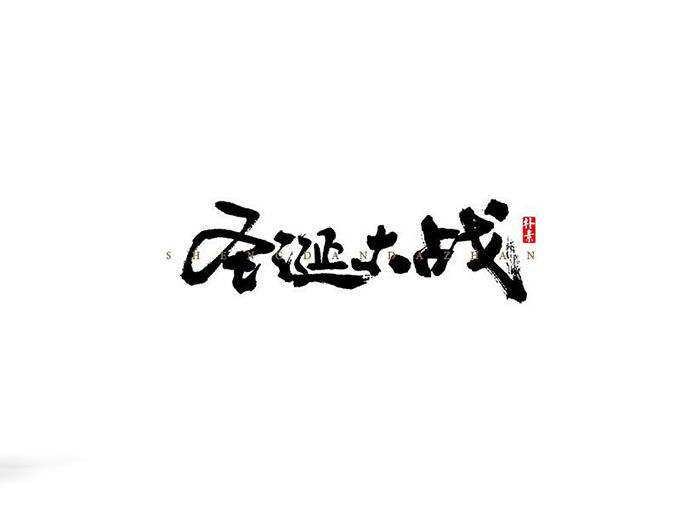
汉字设计需遵循的原则
汉字创意历经发展,由原始的象征图形逐渐演变至文字符号,是一个逐层递进的过程。通过对汉字创意中字体设计发展所蕴含的规律进行探寻,归纳了一些汉字设计原则,来指导设计及应用。
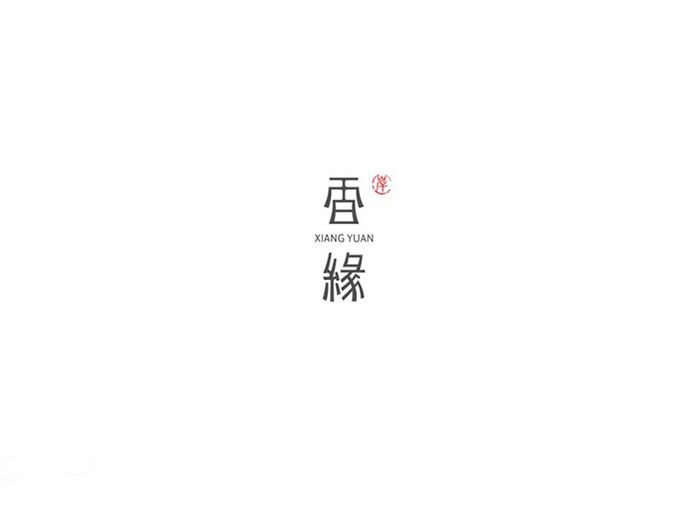
视觉平衡
汉字创意字体设计作为视觉设计的重要部分,设计中需要遵循视觉平衡原则,以塑造作品的美感。主要使用在字体笔划及结构的设计上,笔划运用是字体设计的初始,是决定字体设计风格的主要因素。汉字创意中字体的构成形式多样,通常会依据作品风格的需要而变化,从而形成了其独特的风格。目前,汉字创意字体设计的变化方式主要有叠加、突变、旋转等。
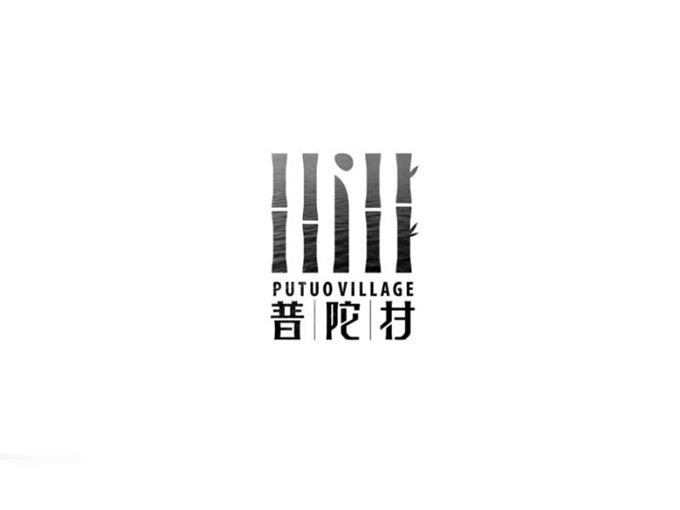
为保证汉字的可辨识性,无论哪种字体设计都应遵循视觉平衡的原则,从而设计出人们看得懂,但又不失新意的字体;字体的结构是设计的关键,基本由点、线、面三个要素构成,讲求匀称、和谐。在字体设计时,只有遵照形式规则将字体结构设计与图形视觉的美感有效的融合在一起,才能使创意汉字更具艺术魅力,展现得体而优美。这一规则就是视觉平衡,这既是汉字自身结构的规律使然,又是符合视觉审美需求的重要表现。
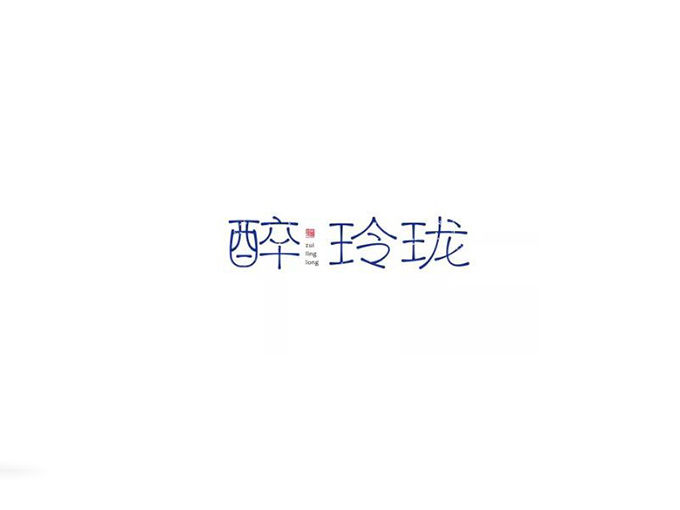
结构得体
字体的结构是汉字创意字体设计中需要着重考虑的因素,其均匀与否很大程度上取决于字形结构。为确保笔划分布均匀,需要兼顾正形呈现与负形空间,来实现字体设计应有的审美价值。创意设计要合理的进行笔划布局,巧妙的将元素穿插在一起,以尽可能的均衡正负形。
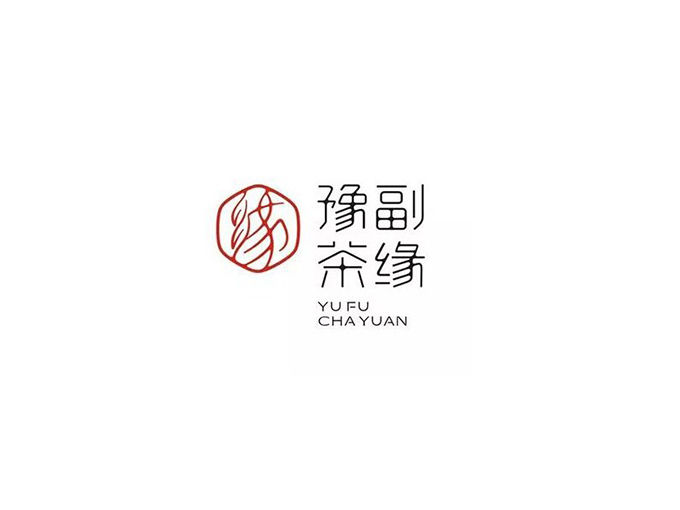
为考虑字形和笔划疏密过大,而避免造成字体结构出现给观众在阅读上带来的误差。因此,合理分析华人的汉字阅读习惯,必须提升设计字体的观赏性,要合理的调整汉字笔划,统一字形和字体大小,使得字体设计笔划得体,结构均匀。
重心稳固
重心稳固与否是衡量汉字创意中字体设计审美的标准之一,会直接影响到字体的可识别性。当字体设计重心稳固时,字体的可识别性强,有助于人们顺畅、舒适的阅读。反之,字体设计重心不稳固则可能会致使人们的视线在视觉范围内上下滑,给人们的阅读造成了一定的困扰,容易产生疲劳感。
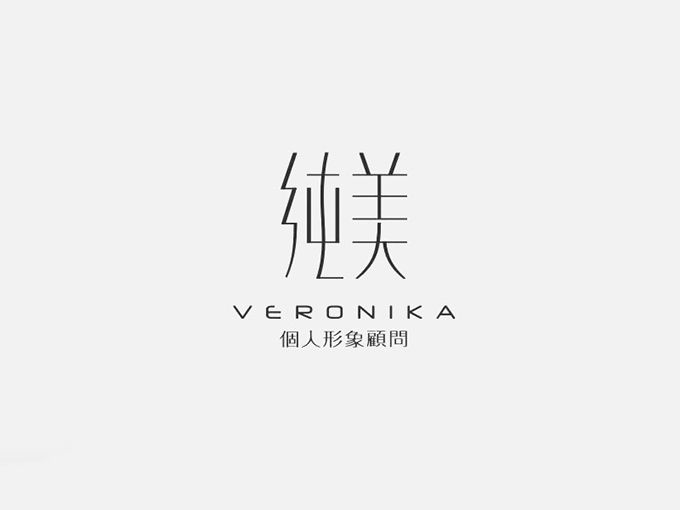
相对于西方文字,汉字的结构特异性强,内涵信息更丰富,要在不断的实践探索中,认真分析、总结以往的设计经验,来正确处理字体重心。另外,重心稳固原则还需要处理好字体重心与字体中心的内在联系,两者即有不同却又存在着必然的联系。纵然汉字字体的书写笔划略显复杂,但可以通过寻找字体外形和中心的方式,确立汉字重心结构,继而实现轮廓内部结构稳固。
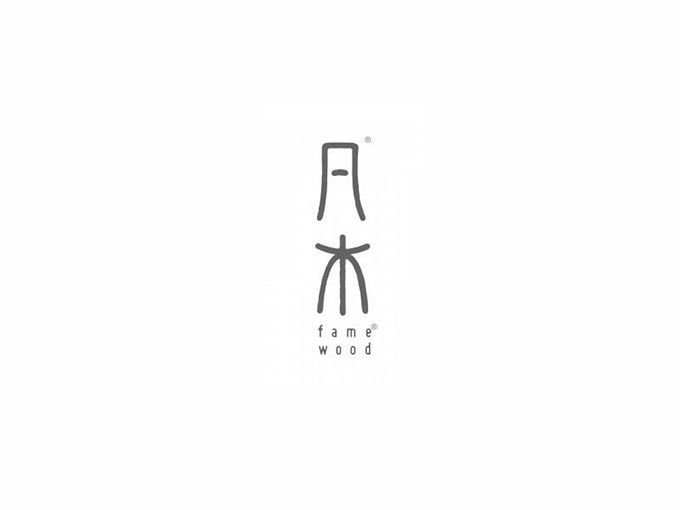
意和谐
汉字由象形文字到简体文字的演变历程中,都是以传达信息的视觉符号形式出现,决定了其形意结合的特性。在视觉层次上,设计字体可以是一种符号,也可以是一组线条,还可以是一个感知图像,它作为造型设计语言应具有传达信息的功能。要始终坚守形式美与信息准确的相辅相成作用,充分发挥出汉字形、意、要素,即设计中需遵循形意和谐原则,从而设计出现代韵味的字体。
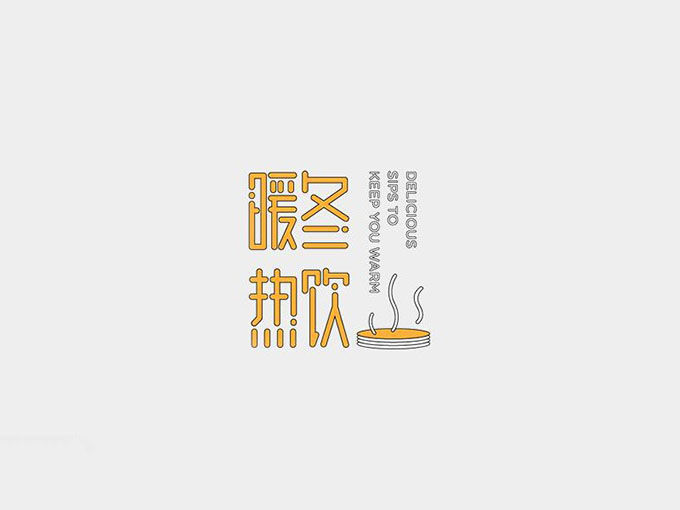
汉字设计的具体应用
汉字创意中字体设计是一个汉字个性化的过程,被广泛应用于现代设计中。在上述原则的指导下,以标志设计与海报设计为例,来对具体应用的探讨。
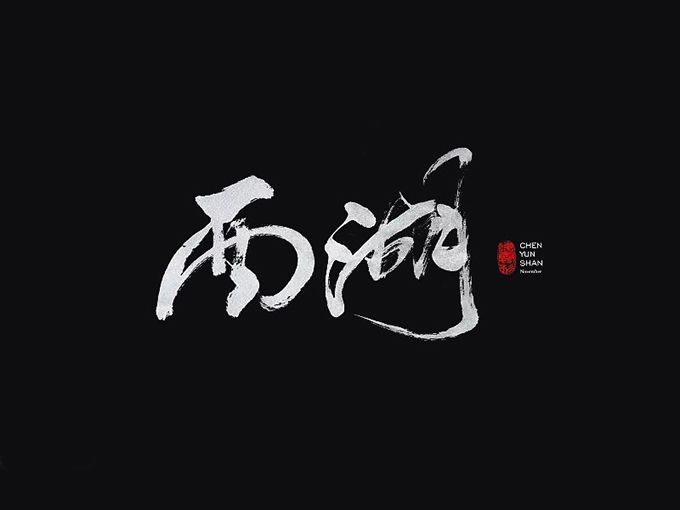
标志设计中的汉字
汉字本身就由形、意、要素构成,笔划结构穿插的特点使其创意字体设计可以直接当作标志来使用。标志设计中汉字创意字体的应用赋予了汉字新的含义,展示了企业的文化理念和品味,塑造了企业的特色形象。另外,汉字创意字体在企业标志设计中的应用,是由一个文字向形象标识转化的过程,有助于企业品牌定位更加精准。
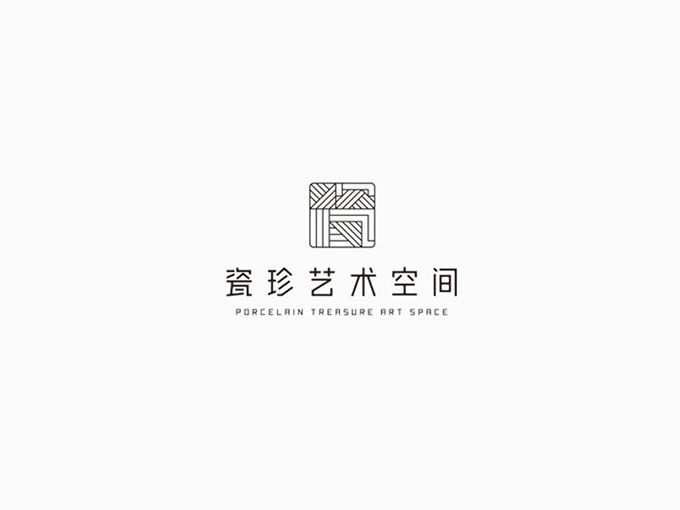
关于汉字创意字体在标志设计中的应用实例不胜枚举,例如重庆城市形象设计,就蕴含了该市以人为本的精神理念;杭州的城市形象设计中,就凸显了其五水共导的特点等。这些标志设计中无不蕴含着丰富的文化意蕴,是汉字创意字体设计的精华所在。在标识设计中使用汉字创意元素时,要注意遵循汉字创意设计的基本原则,了解设计项目所要表达的文化内涵或精神理念,结合并突显行业的特点,合理的规划字体结构、稳固字体重心、表现形意,确保观众视觉上的平衡性、舒适性,从而设计出极具新意的汉字标识,使汉字与图形化完美结合统一。
海报设计中的汉字
海报是我们日常生活中最常见的广告形式之一,其设计中创意字体的应用,补充强化了海报信息,作为其视觉传达的重要元素之一。遵照上述汉字创意字体设计形意和谐的原则,具有形意结合的特征,所以即可作为个体单独出现,又可配备一些图像使用。几乎在所有的平面海报设计中,图像与文字是基本的构成要素,而文字的使用更是必不可少。
在当前生活节奏不断进步的今天,人们对信息传达的效率要求更高,希望在最短的时间内更快、更准确的抓住海报所需表达的主题信息。因此,在汉字创意时,要保证设计字体所传达的信息简洁适中,尽可能的达到一目了然的效果。除此之外,还需注重凸显创意的效果,深化汉字创意字体的韵味,展现出汉字文化的博大精深,智慧如海。
充分了解汉字的结构,把握好其中的规律,在遵循上述四项基本原则的基础上,结合汉字本身所具有的形式之美与内涵之美以及传统文化审美的节奏、韵律等,对汉字字体进行解构与重组,从而提升汉字创意字体的视觉冲击力,达到信息传达与审美的目的。满足当今信息化时代中不断发展进步的人们,以更高效便捷的信息传达方式及载体,作为标准要求应具有重要的现实意义。